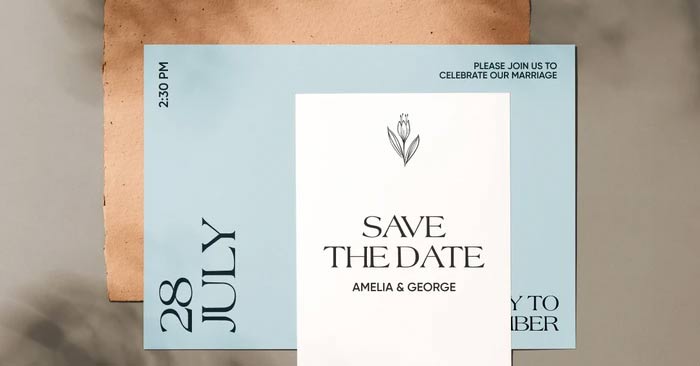
Những kiểu font chữ đẹp cho thiệp cưới, đám cưới
Từ lời mời đến biển báo địa điểm, nội dung đóng vai trò lớn trong việc định hình ngày cưới của bạn. Để tạo ấn tượng đầu tiên tuyệt vời và tạo không khí thanh lịch và lãng mạn, bạn cần có font chữ cưới phù hợp.
Font chữ thiệp cưới
Có ba kiểu phông chữ chính phù hợp với đám cưới: Script, Serif và Sans Serif. Bạn cũng có thể thử nghiệm các phông chữ độc đáo, lạ mắt để tạo ấn tượng đặc biệt.
Tin tốt là bạn không cần phải dành hàng giờ để cuộn qua hàng trăm phông chữ để tìm ra font chữ đẹp nhất… Bài viết này sẽ giới thiệu cho bạn 15 phông chữ cho ngày trọng đại, đồng thời, giúp bạn tìm ra những phông chữ phù hợp với phong cách đám cưới của mình.
Chọn font đám cưới phù hợp
Để biết phông chữ nào là tốt nhất để tạo nên tông màu cho đám cưới của bạn, bạn cần hiểu các phong cách khác nhau của font đám cưới thường dùng.
• Phông chữ Script là lựa chọn cổ điển vì chúng mô phỏng chữ viết tay, thêm nét cá nhân và cảm giác sang trọng, đẹp đẽ với nét vẽ tinh tế.
• Phông chữ Serif và Sans Serif ít trang trọng hơn một chút và dễ đọc hơn. Chúng rất phù hợp với các thiết kế nhiều chữ hơn.
• Bạn có thể chọn phông chữ Serif nếu muốn duy trì tính thẩm mỹ truyền thống và vượt thời gian, trong khi phông chữ Sans Serif mang lại vẻ ngoài hiện đại và sạch sẽ hơn.
• Các phông chữ có kiểu dáng độc đáo, chẳng hạn như phông chữ trong trình tạo font của Picsart, rất tuyệt nếu bạn thực sự muốn nổi bật.
Kết hợp các loại phông chữ khác nhau cho phép bạn tối đa hóa khả năng đọc và tạo ra thiết kế thanh lịch, cao cấp. Ví dụ, bạn có thể sử dụng phông chữ phức tạp hơn cho tiêu đề và phông chữ rõ ràng hơn cho phần thân văn bản.
Font chữ góp phần tạo nên sắc thái cho ngày đặc biệt của bạn. Bảng dưới đây sẽ cung cấp cho bạn hướng dẫn sơ bộ về kiểu phông chữ chính nào phù hợp với kiểu thẩm mỹ đám cưới khác nhau.
Các kiểu font chữ đẹp cho đám cưới
Những font chữ đám cưới được yêu thích nhất trong năm 2024
Font chữ đám cưới độc đáo
1. Fraktur
Nếu đang tìm kiếm thứ gì đó mộc mạc hơn một chút, Fraktur thực sự sẽ thu hút sự chú ý của bạn. Với phong cách gần như gothic và nhiều cá tính, đây là phông chữ tuyệt vời để tạo ra những lời mời đám cưới độc đáo.
2. Lefthanded
Lefthanded là kiểu phông chữ nghệ thuật với các chữ cái có hình dạng độc đáo trông giống như được viết tay. Sử dụng phông chữ này để tạo sự kết nối chặt chẽ hơn với khách bằng cách thêm sự ấm áp và chân thực vào các thiết kế của bạn.
3. Double Struck
Double struck bao gồm các chữ cái có hai dòng trông giống như được vẽ bằng tay. Đây là phông chữ hoàn hảo cho những ai muốn có vẻ đẹp tối giản và hiện đại cho đám cưới, nhưng muốn thêm nét nghệ thuật.
Font chữ đám cưới theo kiểu viết tay
1. Romanticly
Romantically, đúng như tên gọi, là phông chữ lý tưởng để tạo nên bầu không khí lãng mạn. Với phong cách đẹp, gần như viết tay, phông chữ này mang lại cảm giác như một bức thư tình mới viết. Đây là một trong những phông chữ đẹp nhất cho thiệp mời đám cưới!
2. Candlescript
Với các chi tiết trang trí trên chữ in hoa và các chữ cái lớn trải dài, Candlescript mang đến cảm giác kịch tính và hùng vĩ cho bất kỳ thiết kế đám cưới nào. Phông chữ này vẫn rất dễ đọc nên là lựa chọn tuyệt vời cho mọi thứ, từ biển báo đến sơ đồ chỗ ngồi.
3. Clattering
Là một phông chữ viết tay đậm, Clattering nổi bật giữa đám đông. Sử dụng phông chữ này một cách tiết kiệm trên các thiệp mời đám cưới hoặc thiệp cảm ơn để tạo ấn tượng! Bạn cũng có thể kết hợp phông chữ này với một chú thích mạnh mẽ tương đương trên Instagram để thực sự nắm bắt được sự kỳ diệu.
4. Flanella
Flanella được vẽ bằng những đường nét tinh tế với nhiều chi tiết trang trí. Điều này khiến phông chữ này trở thành lựa chọn lý tưởng để tạo thêm cảm giác kỳ quặc và quyến rũ cho thiệp mời đám cưới, biển báo và các yếu tố trang trí khác.
Font chữ đẹp Flanella
Font Serif truyền thống
1. Libertinus
Với các chữ cái gọn gàng và đường nét chặt chẽ, Libertinus mang nét truyền thống khiến nó trở nên lý tưởng cho các lời mời đám cưới cổ điển, biển báo và sơ đồ chỗ ngồi. Kết hợp với phông chữ viết tay để có thiết kế vượt thời gian mà bạn không thể bỏ qua.
2. Yesterday
Yesterday là một phông chữ hiện đại vẫn giữ được cảm giác hoài niệm lãng mạn. Hoàn hảo cho đám cưới truyền thống, sử dụng phông chữ này trên các lời mời, biển báo và nhiều thứ khác để tạo mối liên hệ cá nhân với khách mời.
3. The Paloma
Là một phông chữ tối giản và dễ đọc, The Paloma hoàn hảo cho các đám cưới cổ điển, giản lược. Bạn cũng có thể kết hợp nó với các phông chữ phức tạp hơn để tạo sự tương phản tinh tế.
4. Morgin Astera
Morgin Astera là một phông chữ sạch sẽ nhưng vẫn thu hút được ánh nhìn vì nó có các chi tiết trang trí trên một số chữ cái. Do đó, đây là lựa chọn tuyệt vời cho nhiều lời mời khác nhau. Bạn cũng có thể sử dụng phông chữ này trong biển báo vì nó trông tuyệt vời ở kích thước lớn.
Phông chữ Sans Serif hiện đại
1. Amore
Amore mang đến nét hiện đại cho kiểu phông chữ cổ điển và vượt thời gian. Phông chữ này hoàn hảo cho những đám cưới xa hoa, nơi mục tiêu là tạo cảm giác sang trọng, lộng lẫy. Sử dụng font đám cưới này trong các bài đăng trên mạng xã hội để nổi bật.
2. Vermina
Với các chữ cái ghép lại và kiểu dáng bo tròn đẹp mắt, Vermina tạo cảm giác lãng mạn, phóng khoáng khi sử dụng trên thiệp mời đám cưới và các tài liệu khác.
3. Olive
Một phông chữ tối giản nhưng phong cách, Olive lý tưởng để tạo biển hiệu đám cưới sang trọng và đồ họa mạng xã hội. Phông chữ này cũng là sự bổ sung hoàn hảo cho các font phức tạp hơn vì không giống như kiều font Sans Serif khác trong danh sách này, nó truyền thống hơn.
4. Melody Southern
Melody Southern là bộ đôi phông chữ nổi bật. Kiểu chữ in hoa đậm và cổ điển trong khi kiểu chữ nghiêng lãng mạn và mang cảm giác cá nhân. Sử dụng những phông chữ này nếu bạn muốn có một cặp phông chữ phù hợp để sử dụng trên tài liệu đám cưới của mình.